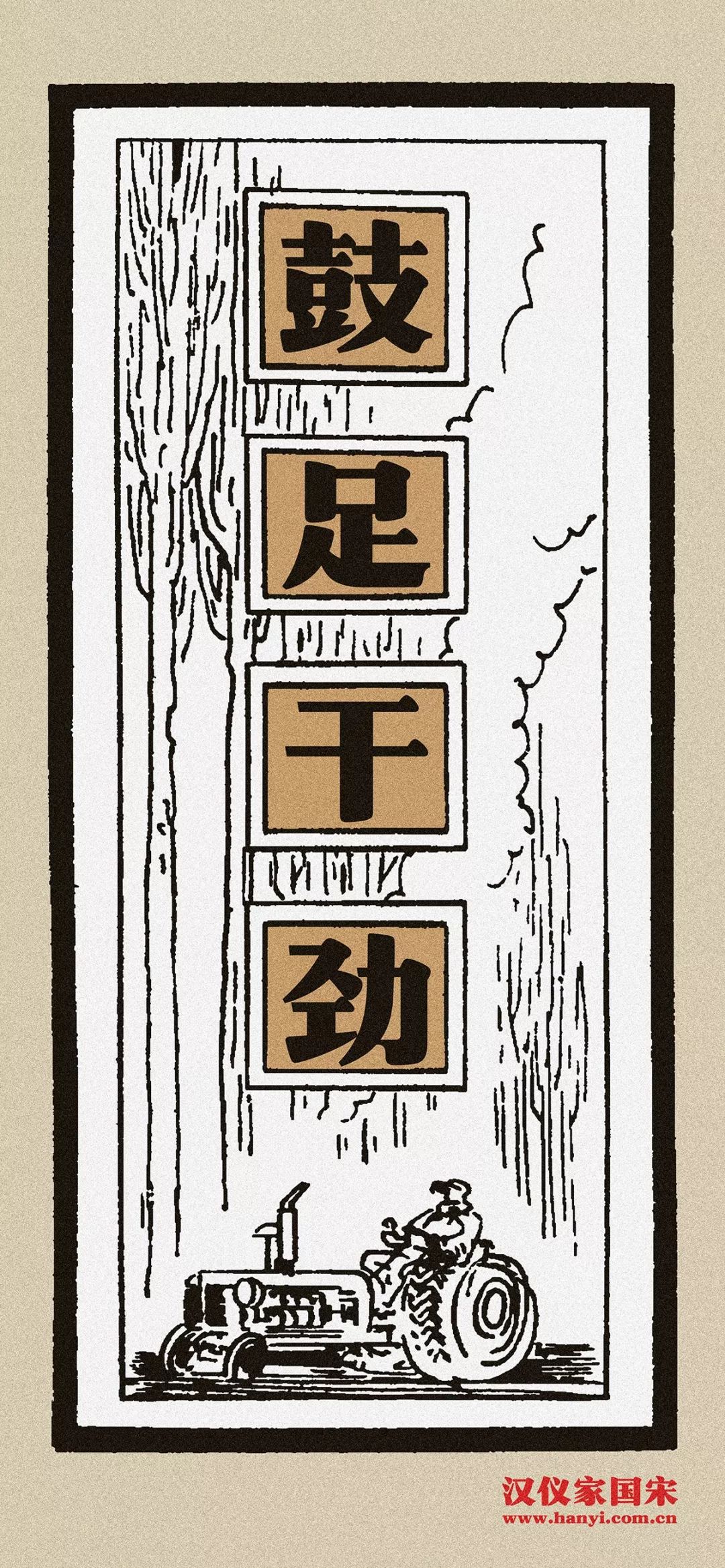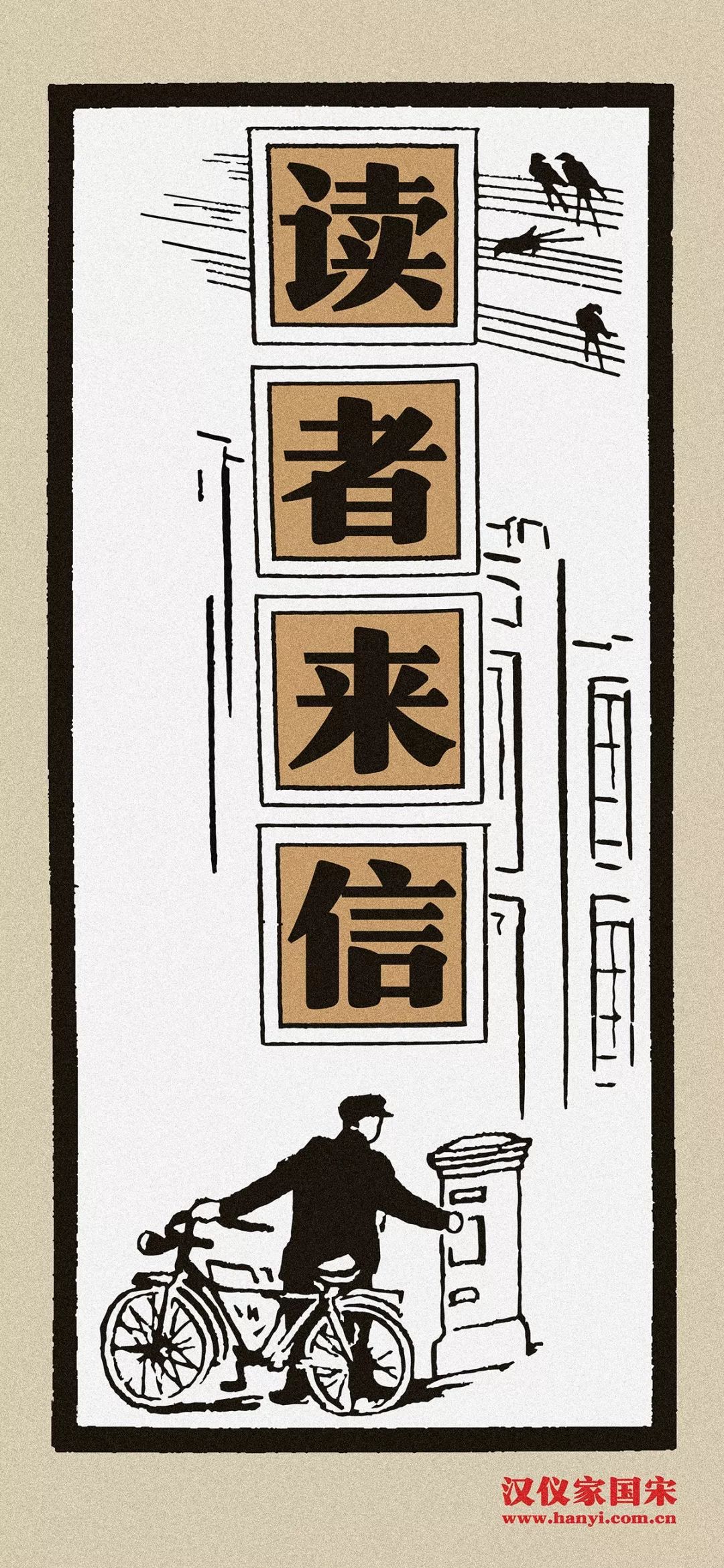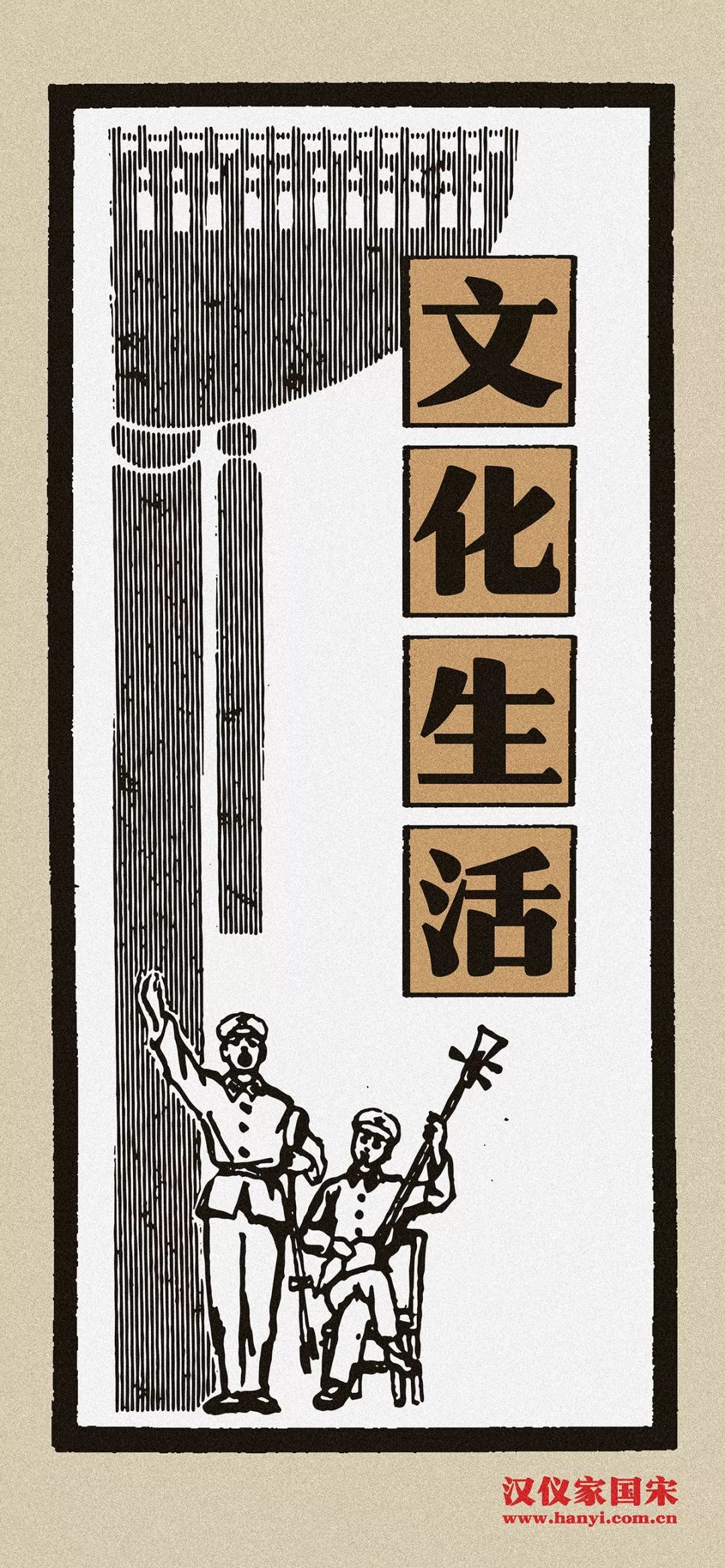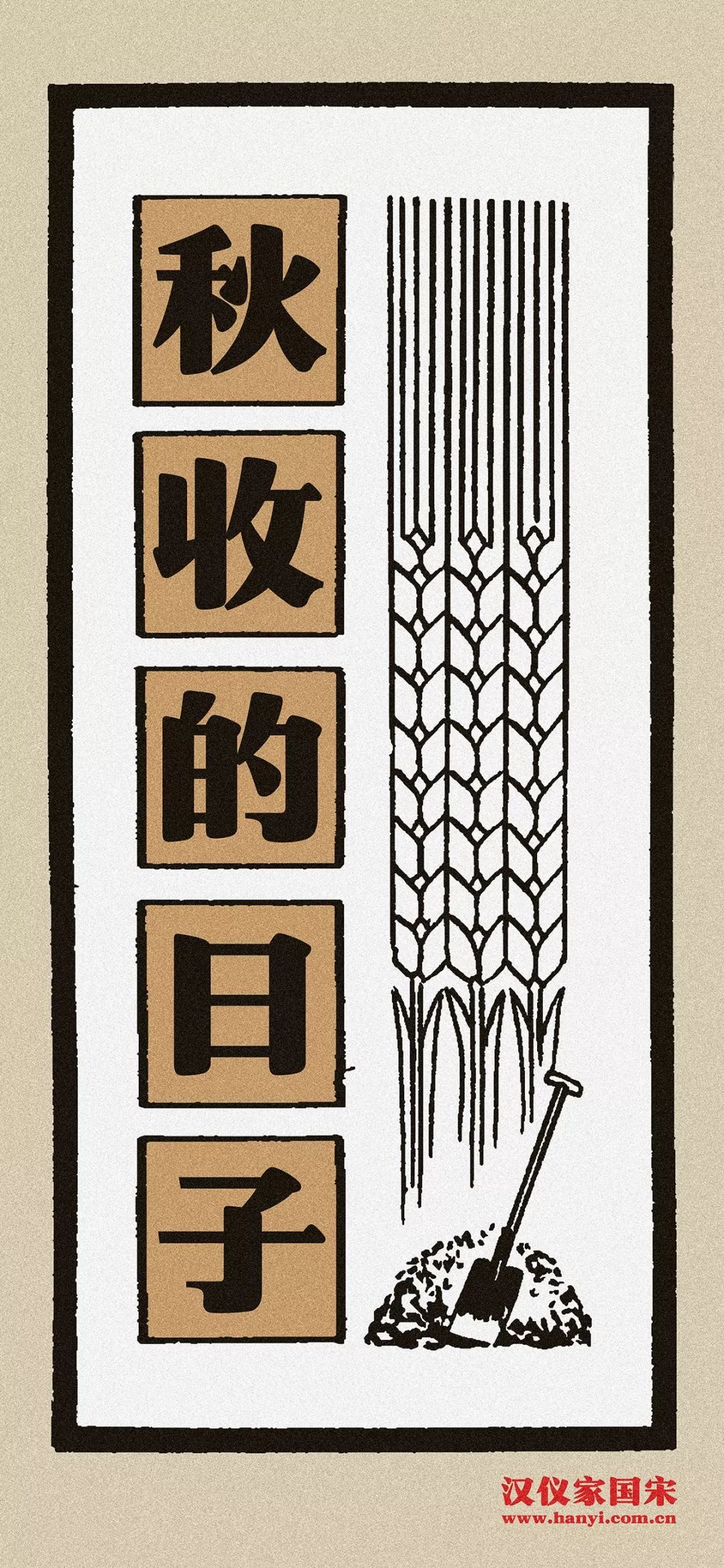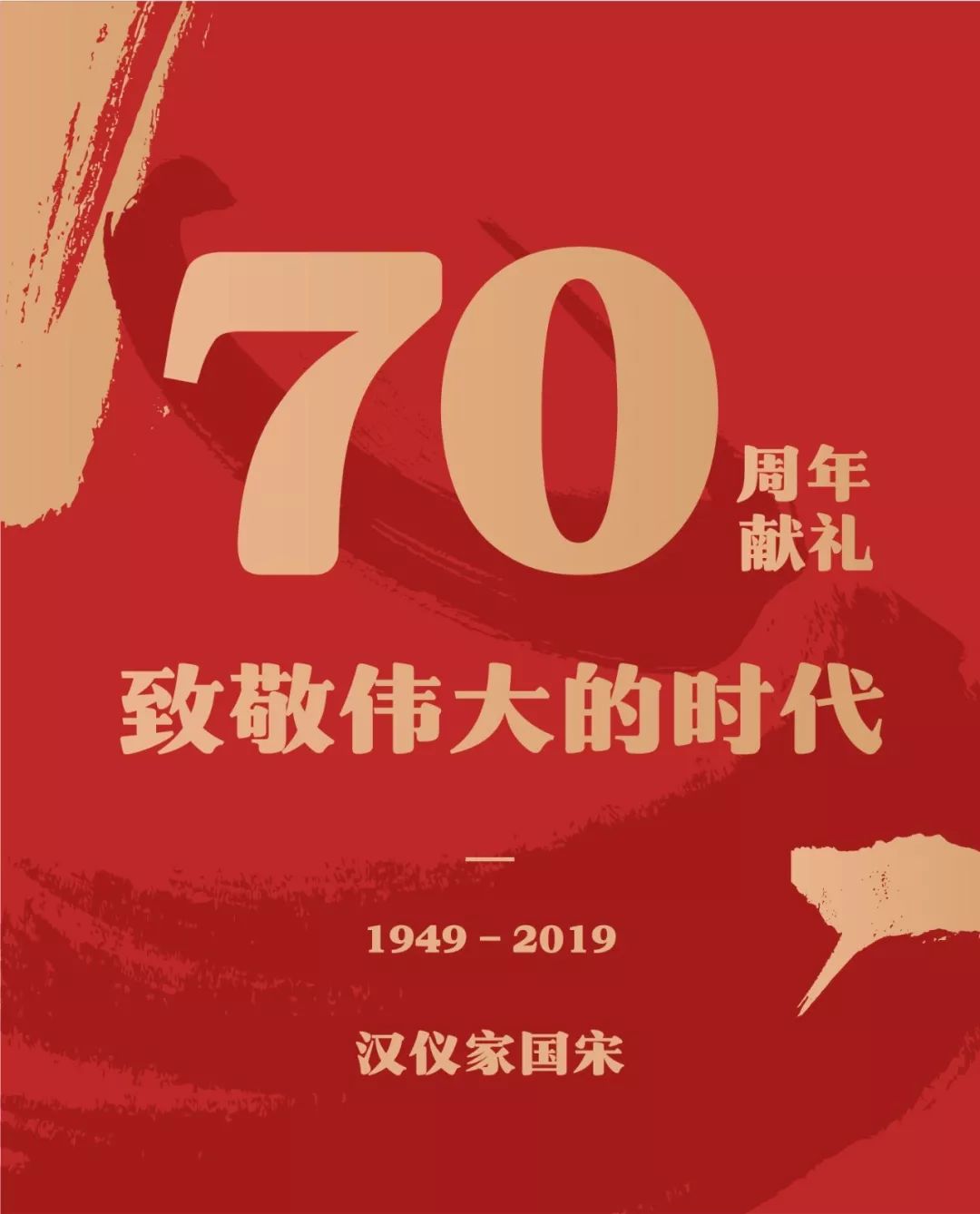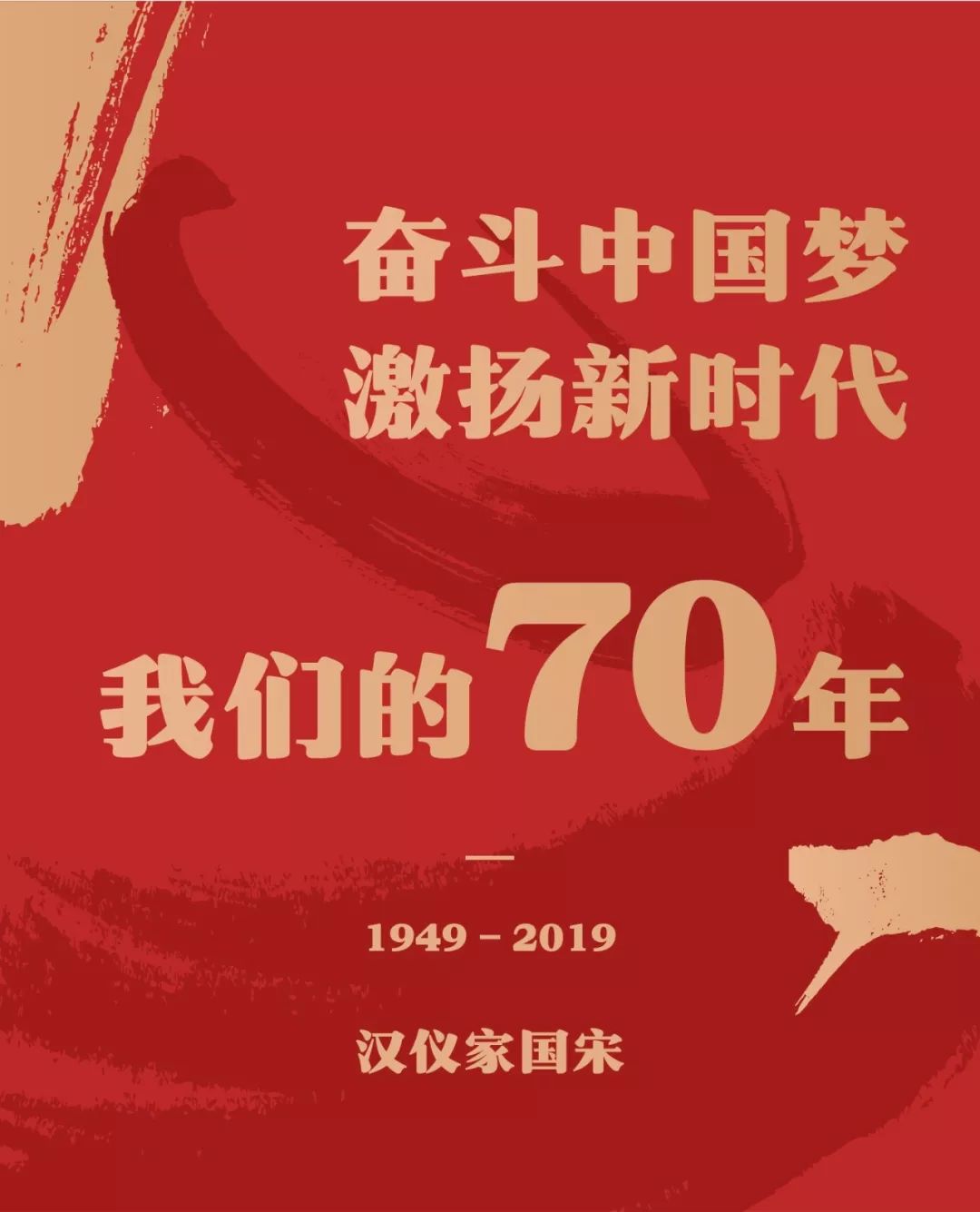
汉仪家国宋字体介绍,汉仪家国宋设计思路
我们张开双臂拥抱时代精神,
我们用笔墨承担责任与使命,
不负时代,有所作为,
国庆特别策划 —— 汉仪家国宋,
献礼新中国成立70周年!
致敬伟大的时代!
设计的发展离不开环境的变化,不同的时代精神赋予了设计不一样的生命力。改革创新是时代精神的核心,新时代中国特色社会主义是我们党领导人民进行伟大社会革命的成果,那么新中国的时代精神赋予了设计怎样的精神面貌呢?
(一)
纵观设计发展史,不乏政治思潮和政治生态对设计风格的发展产生影响的例子。著名的俄国构成主义设计运动,是在俄国的一小批先进知识分子中产生的前卫艺术运动,是一场典型的设计强调为政治服务的运动。俄国十月革命的成功使马克思主义得到了实践的认可,他们投身于社会革命,积极探索工业化的设计语言,希望利用自身的知识服务于当时的政权。
(第三国际塔)
塔特林的第三国际纪念塔,堪称为当年时代精神的纪念塔,希望通过电报、电话等无线电通讯手段向外界发布新闻、公告和宣言,但是他的设计思想没有受到无产阶级的理解和接纳,最终无法得到实践。
受俄国十月革命影响的陈独秀创办的《新青年》杂志代表了中国革命时期的先进思想。书籍作为传播知识的载体,形式设计能够反映出内容的核心思想,让人耳目一新的字体设计可以看出这一批先进人物对于新事物、新思想的追求。
(新青年杂志封面)
抗日战争全面爆发后,中国共产党高举抗日民族统一战线的大旗,实施民主自治,吸引了大批知识分子前往革命圣地 —— 延安,成为影响革命时期字体设计风格的重要因素。
(中国共产党第七次全国代表大会旧址)
当时盛行于上海等地的先进设计思想被带到了延安,经受革命洗礼后,美术字的设计呈现出了另外一种面貌。毛泽东在《在延安文艺座谈会上的讲话》中指出“我们的文学艺术都是为人民大众的,首先是为工农兵的,为工农兵而创作,为工农兵所利用的。”中国共产党强调设计为人民服务,字体的创作首先要考虑人民的接受度,因此美术字在延安的发展变得更加简洁明了,严肃醒目。
(1938年7月1日,在延安欢迎世界学联代表。)
(二)
新中国成立以后进行了大规模的社会主义建设,“美术字”成为宣传工作中广泛使用的一种字体,此时的设计风格基本已经趋于成熟,不仅要求整齐美观,更重要的是可以利用其清晰、严肃、醒目的特征为人民群众的宣传教育工作更好地服务。
应用最广的美术字就属“老宋体”了,这种字体庄严有力、稳重权威,会使人产生明朗而严肃的感觉,非常适合宣传口号标语,有着非常重要的积极意义。
(50年代老宋体变形美术字)
当时的美术字承载了宣传教育的使命,为了普及书写方法及规则,还出版了大量的书籍教材。
(美术字教程类书籍)
这个时期的美术字有几个标准:一、清楚工整;二、粗壮醒目;三、严肃活泼。不管美术字的变化有多繁多,但是都有一个统一的标准,就是辨识度高,可以让人民群众一望而知,坚持全心全意为人民服务是中国共产党的一贯宗旨。
(50年代宣传标语)
革命时期的美术字设计到新中国成立后逐渐形成了成熟的风格,坚持严谨、工整、朴实、醒目、严肃、活泼的特点,不能单纯的追求形式上的美观,更要做到美术字大众化。见微知著,字体的变化可以反映出设计的家国情怀,心怀人民,天下为公。
(天安门前的宋体字)
社会高速发展,如今使用字体的场景更加丰富复杂,形式更加多样化,但字体设计的初衷是一样的,当今的字体设计,依旧承担着时代的责任与使命,挖掘时代精神,传承家国情怀!
(三)
汉仪家国宋,是一款具有新中国时代精神的标语字体,他传承了当年美术字的革命气息,圆润饱满的字型与传统严谨的宋体结构相结合,为这款字营造出一种醒目、沉稳、奋进、质朴的气质,设计灵感源于为人民的艺术,最终服务于人民。
字体特征解析
❶
汉仪家国宋字形方正呈扁式,重心低,稳重而有力。字形特征延续了老宋体美术字的时代感,字身上下各收短5%,字面比例达95%,更加沉稳庄严,稳定厚实。
❷
汉仪家国宋笔画粗重,整体效果醒目而有力。竖笔的起笔收笔倾角规范而严谨,保留了传统宋体字书写笔画时的倾斜特征,竖笔则去除了宋体加锋的装饰特点,让字体的排版效果清晰、简约和易识别。
❸
这款字体的笔画方圆结合,既浑圆饱满又不缺锐利,严肃中不乏活泼。竖弯钩曲线饱满、丰富多样,运用不同弧度的曲线打造出的笔画圆润有力且富有变化。
❹
补充了与中文相匹配的西文设计,用传统的粗衬线体配合宽厚的汉仪家国宋,将扁宽的风格充分融入设计中,方便中西文搭配使用。
字体应用展示
献礼70周年应用展示
“人民需要艺术,艺术更需要人民”,邓小平在《中国文学艺术工作者第四次代表大会》上对艺术与人民的关系进行了高度概括。字体和其他文学艺术形式一样,能够忠实记录下当时人们的思想活动和物质条件。我们通过字体的发展历史,可以看出环境的变化、社会的发展,以及思想的变迁。
新中国成立70周年之际,我们从字体设计的角度来重温这段波澜壮阔的历史,谨以“汉仪家国宋”,鉴往知来。